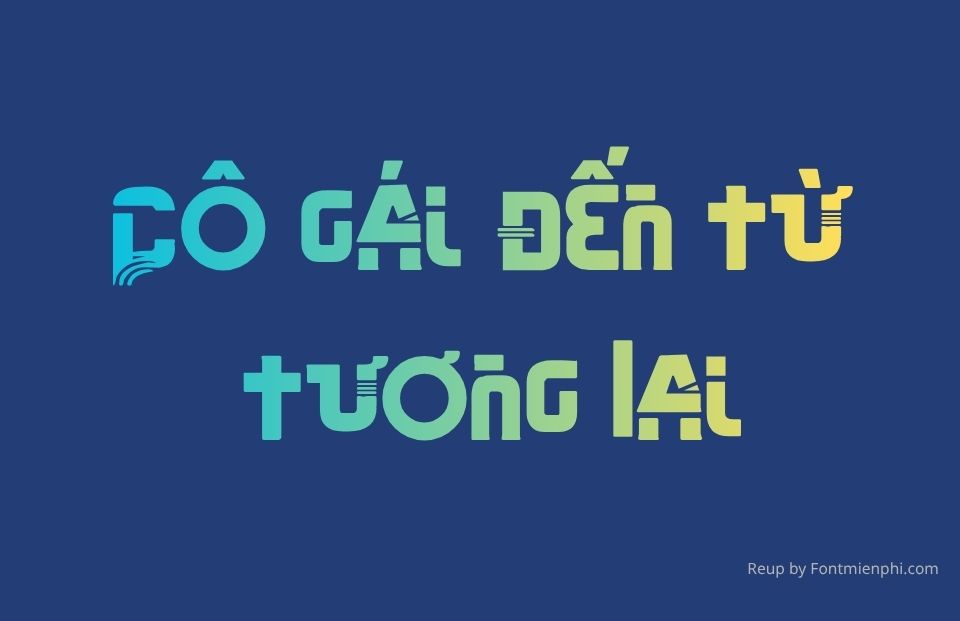
Font Việt hóa 1FTV VIP Shizuoka Cyberpunk – Phong cách công nghệ tương lai đầy cá tính
Font Việt hóa 1FTV VIP Shizuoka Cyberpunk là mẫu font display nổi bật với phong cách Cyberpunk, công nghệ tương lai và Sci-Fi, phù hợp cho những thiết kế cần sự mạnh mẽ, hiện đại và khác biệt. Các đường nét chữ mang cảm giác kỹ thuật số, tốc độ và không khí của những thành phố tương lai rực sáng ánh đèn neon.
Điểm nổi bật của 1FTV VIP Shizuoka Cyberpunk
Shizuoka Cyberpunk sở hữu kiểu chữ góc cạnh, cá tính và có khả năng tạo điểm nhấn rất tốt khi sử dụng ở kích thước lớn. Phiên bản Việt hóa giúp font hiển thị đầy đủ tiếng Việt, thuận tiện hơn cho các designer khi làm poster, banner, thumbnail hoặc nội dung quảng cáo.
Font đặc biệt phù hợp với các chủ đề như:
• Cyberpunk và thế giới tương lai
• Game, eSports và gaming
• Công nghệ, AI, robot
• Poster phim khoa học viễn tưởng
• Thumbnail YouTube
• Banner sự kiện
• Logo và tiêu đề thương hiệu
• Thiết kế thời trang đường phố
• Album, MV và sản phẩm âm nhạc điện tử
Phong cách thiết kế mạnh mẽ và hiện đại
Điểm thu hút của Font Việt hóa 1FTV VIP Shizuoka Cyberpunk nằm ở cảm giác công nghệ rất rõ nét. Khi kết hợp cùng nền tối, hiệu ứng neon xanh, tím, đỏ hoặc các chi tiết glitch, font có thể tạo nên một bố cục mang đậm không khí của thế giới Cyberpunk.
Bạn cũng có thể sử dụng font cho các tiêu đề ngắn, slogan hoặc typography nghệ thuật để tạo cảm giác mạnh và tăng khả năng thu hút người xem.
Font Việt hóa dành cho designer
Với phiên bản đã được Việt hóa, người dùng có thể dễ dàng nhập nội dung tiếng Việt có dấu mà vẫn giữ được phong cách đặc trưng của font gốc. Đây là lựa chọn đáng thử nếu bạn đang tìm kiếm một mẫu font cá tính dành cho các dự án công nghệ, gaming hoặc thiết kế tương lai.
Font Việt hóa 1FTV VIP Shizuoka Cyberpunk sẽ giúp các sản phẩm thiết kế trở nên nổi bật, hiện đại và mang đậm chất Sci-Fi hơn.